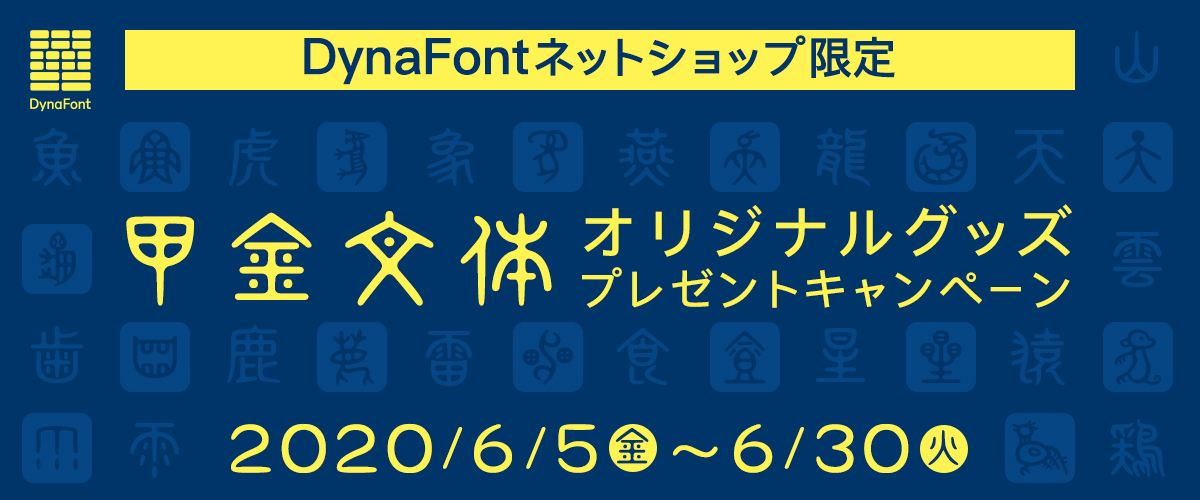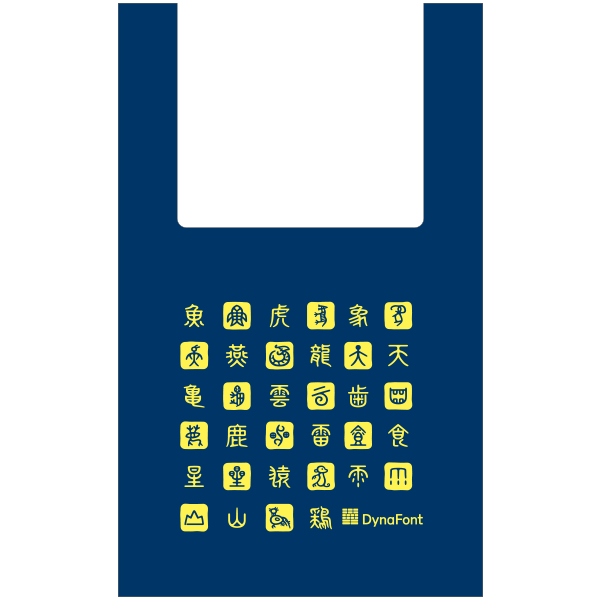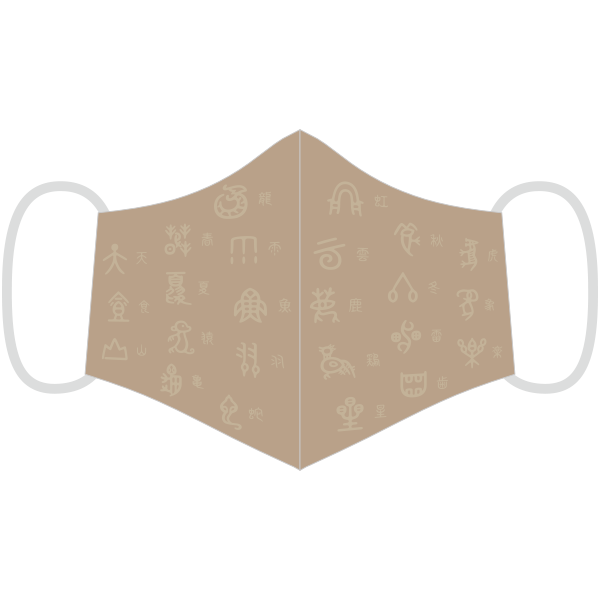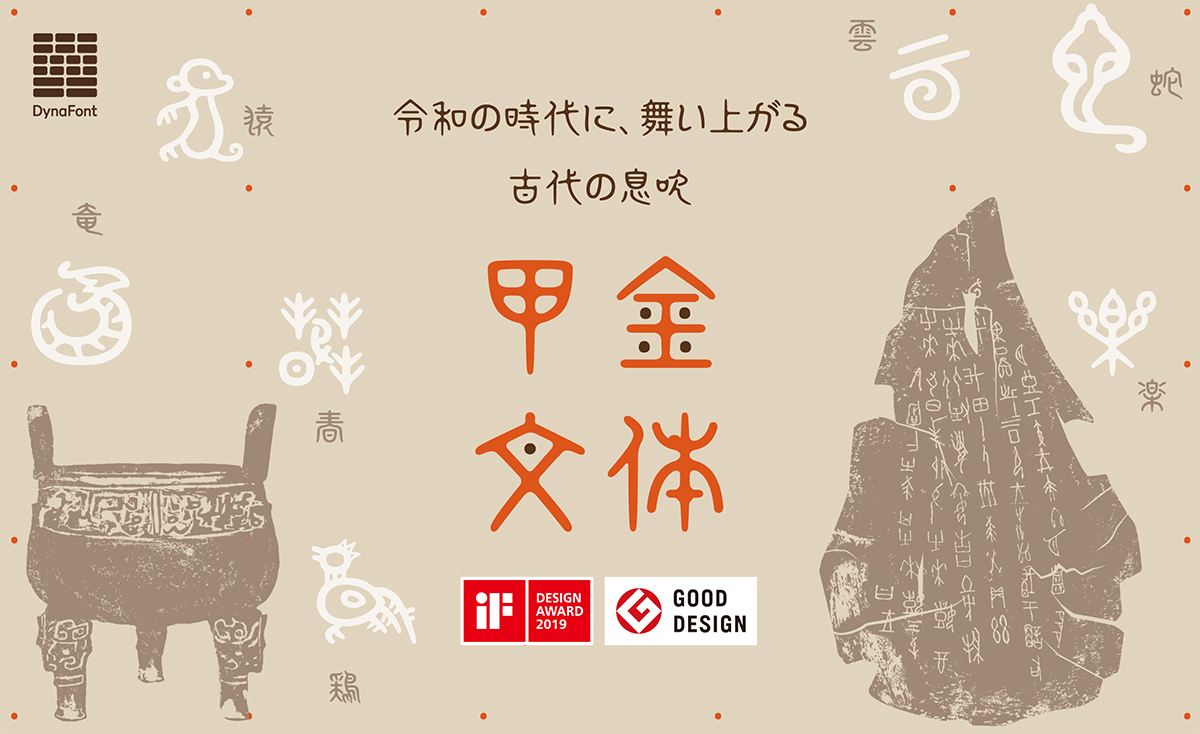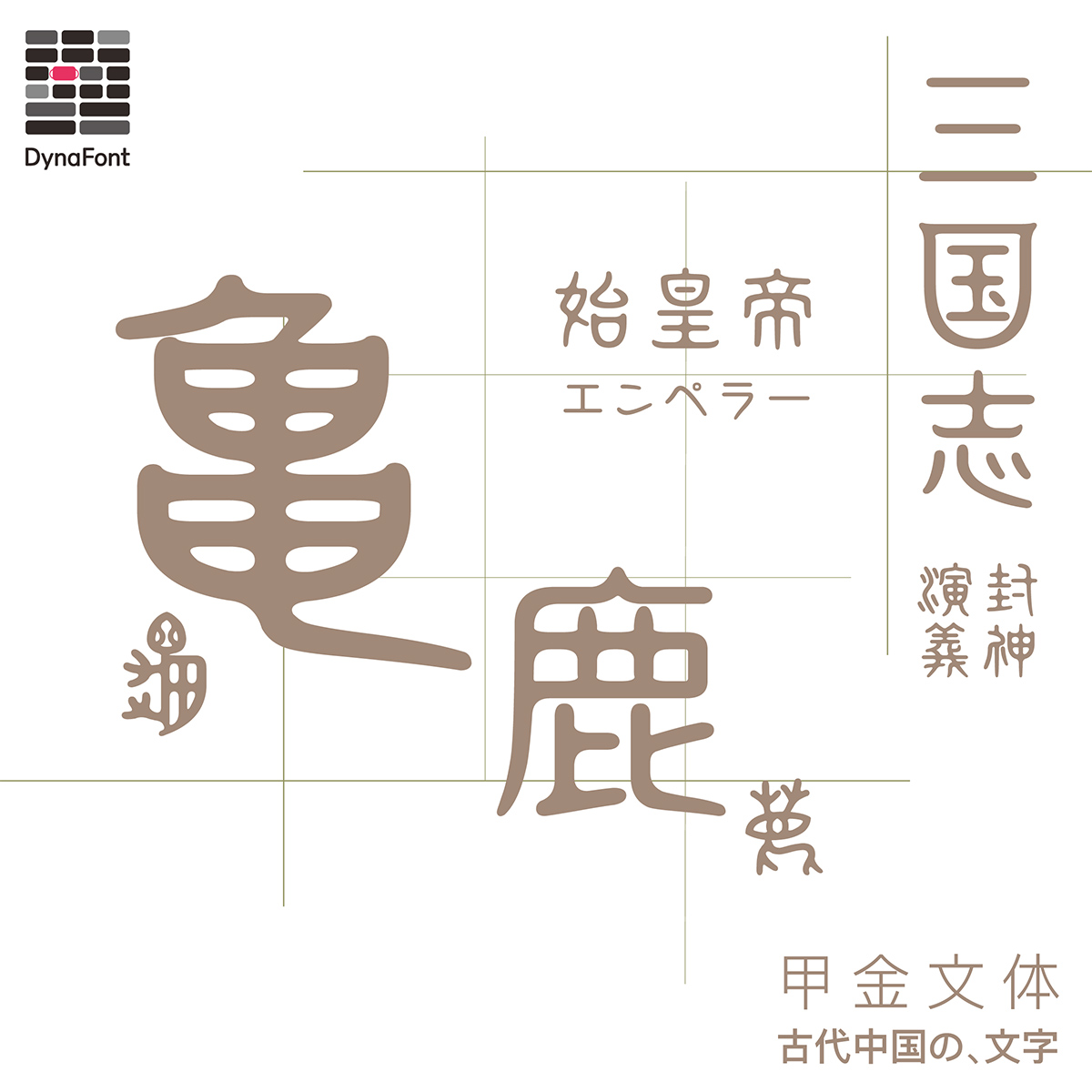
「甲金文体」は、古代文字の美しさに着目し、甲骨文や金文体の特徴である幾何学的な模様を取り入れた素朴ながらも気品さも備えた国内外のアワードを受賞しているダイナフォントの代表書体。
2020年6月5日に行われた「DynaSmartシリーズ」アップグレードにて、「DynaSmart V」での先行収録に続き、「DynaSmart T」にも追加収録された。
今回「DynaSmart T」への収録により、より多くのユーザーに「甲金文体」を使用される機会を得たことで、「甲金文体」をまだ知らない人に知ってもらうため、「甲金文体オリジナルグッズ」として「甲金文体エコバッグ」「甲金文体マスク」を制作したとのこと。
【甲金文体 概要】
難解な先秦時代の古代文字を識別しやすいようにリファインすることで、デジタルフォントにおいても脈々と続く文字文化の素晴らしさが取り入れられている点で高い評価を受けた「甲金文体」は、2018年に「グッドデザイン賞」、2019年には世界的に最も権威あるデザイン賞の1つ「iFデザイン賞(iF Design Award)」を受賞。